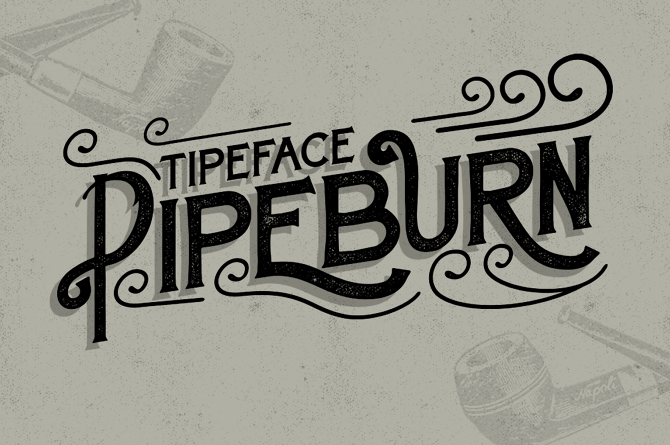
A Pipeburn Typeface é uma obra do designer TypeFace inspirada em um fósforo de tabaco que seu avô possuía. Inspirado no aspecto clássico e moderno, a família decidiu incorporar detalhes que lembram o fumo ao invés da chama propriamente dita para criar uma aparência única e intrigante. O design foi projetado com alternativas estilísticas suficientes para permitir a criação de qualquer estilo personalizado desejado, tornando-a ideal para aplicações variadas como design vintage, postais, marcas corporativas, selos e muito mais.